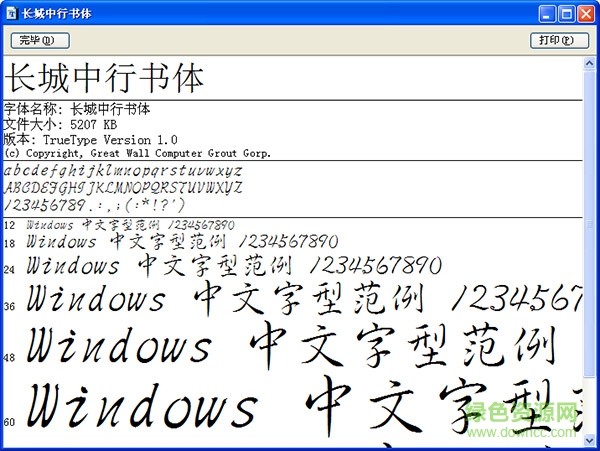
gbhersin medium(長(zhǎng)城中行書體)是一款清晰秀麗的中文行書字體,運(yùn)筆放縱,線條舒展,筆墨濃淡相間,姿態(tài)優(yōu)美漂亮,喜歡的朋友趕緊來綠色資源網(wǎng)下載吧!
一加大橫、豎畫的傾斜度,增強(qiáng)整個(gè)字的動(dòng)勢(shì);
二把方形的字傾斜成斜邊形,從險(xiǎn)勢(shì)中增強(qiáng)字的動(dòng)勢(shì);
三采用倚正相依手法,使字體活潑穩(wěn)定又不東倒西歪;
四采用虛實(shí)對(duì)比手法,使字體取得動(dòng)而平衡的要求。